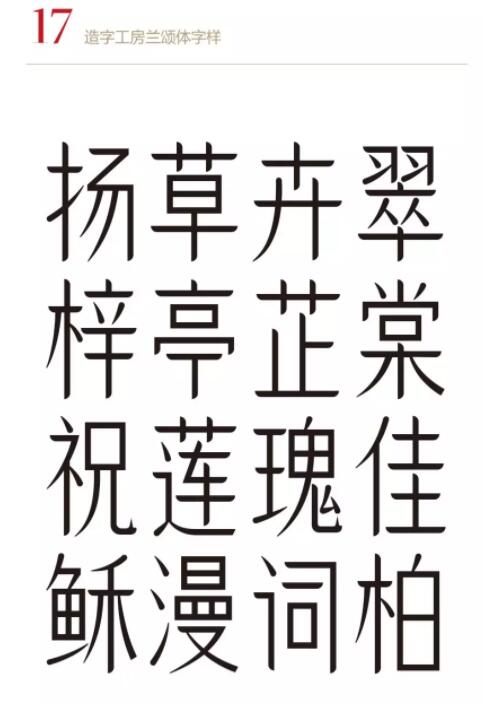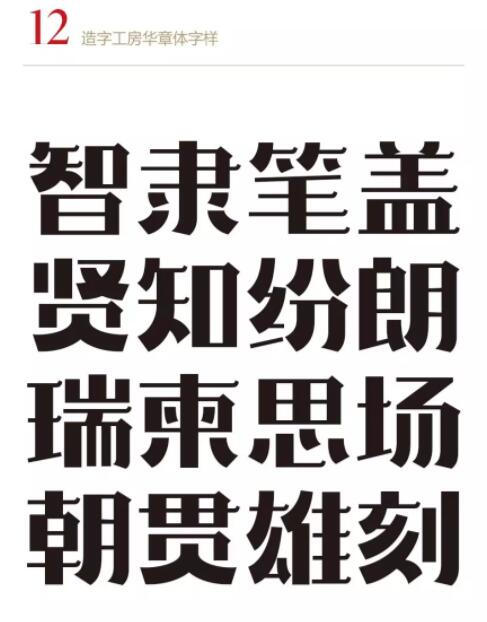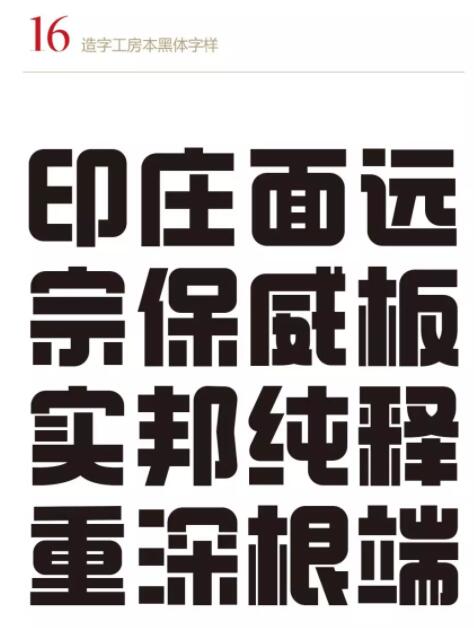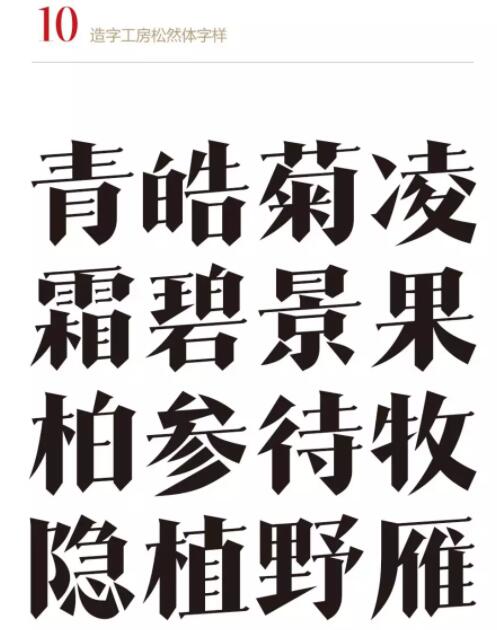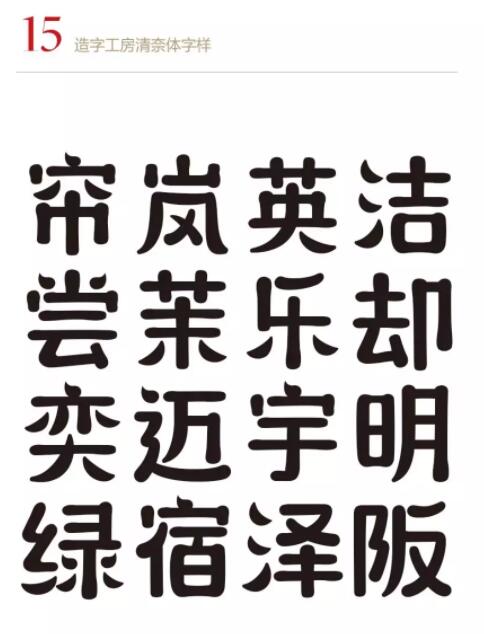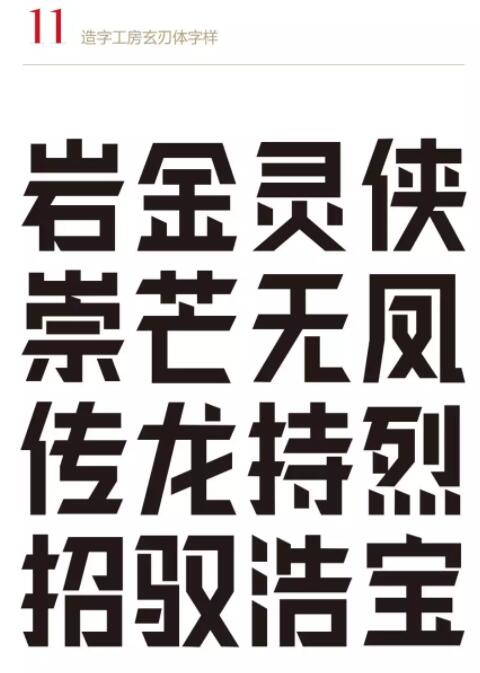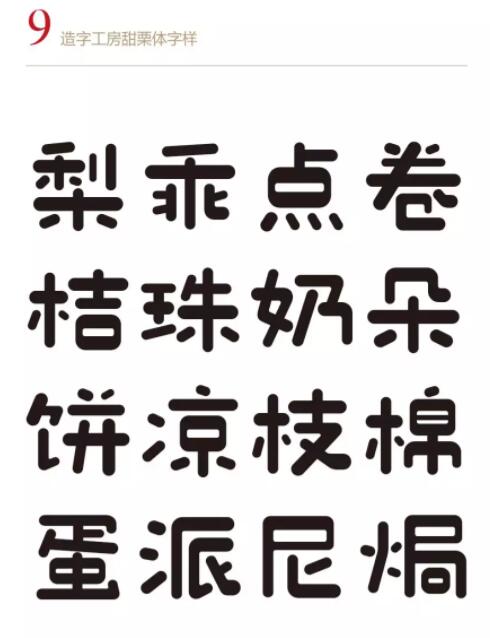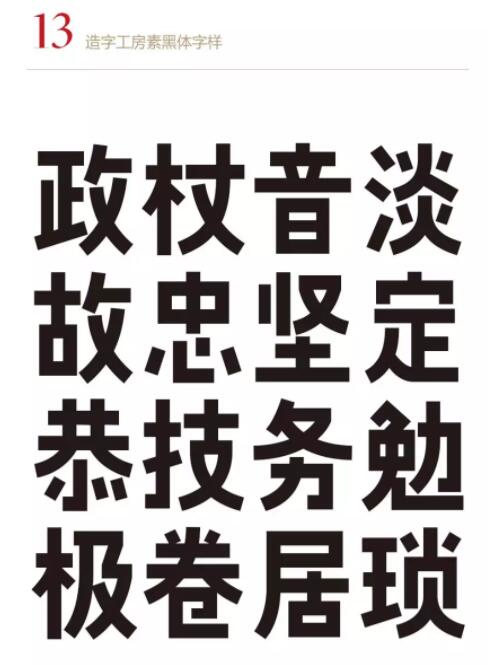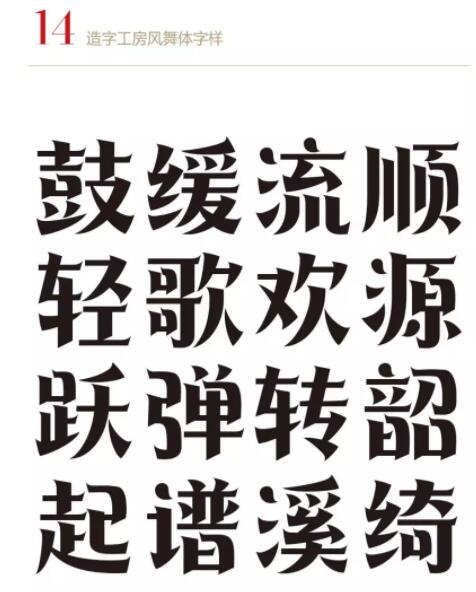
造字工房2020年全新字体产品即将发布
兢兢业业又一年,造字工房已在字体设计的路上走过九个年头!从开始一年仅出品一两款,到目前每年创新近二十款,造字工房已拥有当初近十倍的设计开发能力。今年,我们一如既往,通过整年的倾心打造,造字工房全新十八种字体产品依然如期而至,将于新年之际在官网正式发布,届时,造字工房字体产品将达至九十九种!今年即将发布的十八种全新字体产品或唯美或怪魅,犹如十八般武艺,将使您来年的设计工作更加游刃有余,让我们共同期待!......
全新字体,很快就来!
据悉造字工房这次将发布18款字体。
造字工房夏萤体设计说明
造字工房夏萤体字形修长,较高的重心令其有一种娴雅静穆的静态美感,笔画融畅简爽、流利秀美,结构紧密有致、清秀平和,其字风格温婉妍媚却又不失端庄拙朴之感,兼具现代时尚与传统气韵,韵味十足。适用于大标题及个性品牌设计推广等环境。本字体为简体字库,采用OpenType/CID格式,Adobe-GB1-5编码。基于中华人民共和国GB2312-80字符集标准,另按需添加101个汉字。共收容字数6864CJK汉字,ASCII常用字符100个。